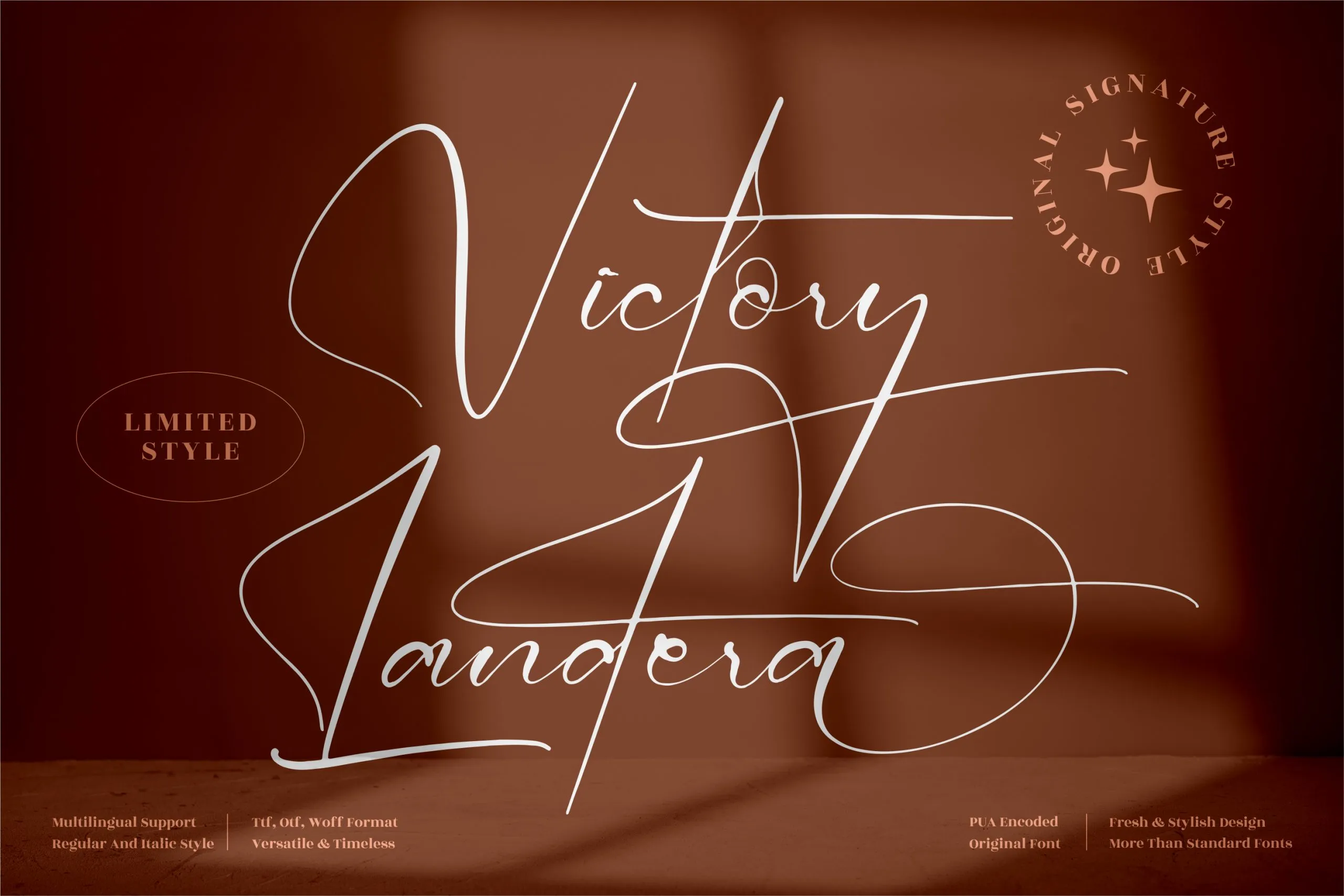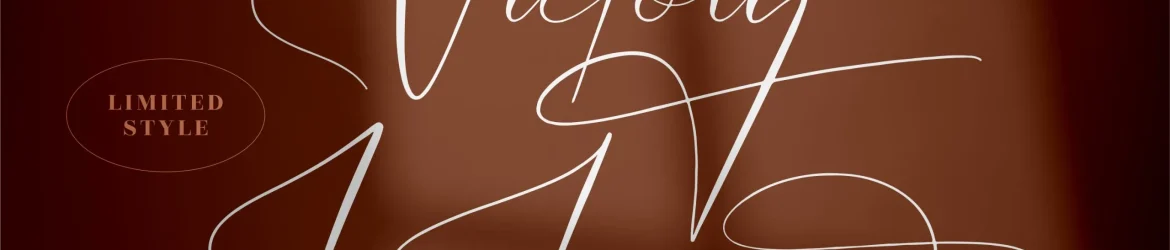
A ‘Victory Landera Font’ é uma elegante assinatura-fonte criada pelo designer perspectype para projetos que exigem um toque de luxo. Seu estilo moderno e sofisticado torna-a uma escolha ideal para uma variedade de aplicativos, incluindo logomarcas, projeto de marcas, designs de móveis, embalagens de produtos, canecas, citações, painéis publicitários, sacolas de shopping, camisetas, capas de livros, cartões de nome, convites e cartões de agradecimento, etiquetas, fotografia e até mesmo marcas para fotos especiais. Seja você um designer gráfico ou criador de conteúdo digital, essa fonte é perfeita para adicionar um toque personalizado aos seus projetos mais requintados. Com sua capacidade única de moldar texto em uma assinatura elegante, a ‘Victory Landera Font’ promete torná-lo o ponto focal de qualquer trabalho de design.